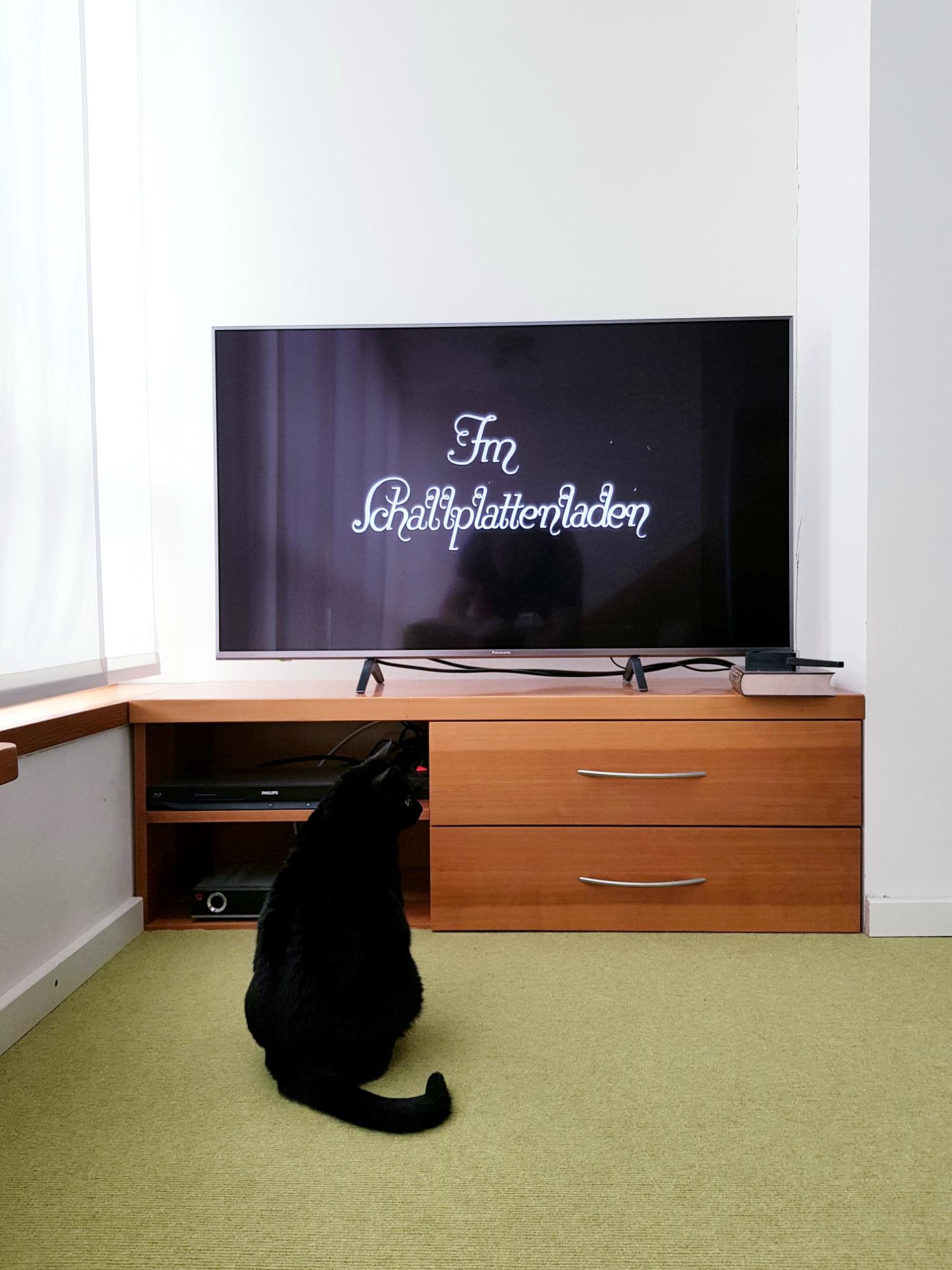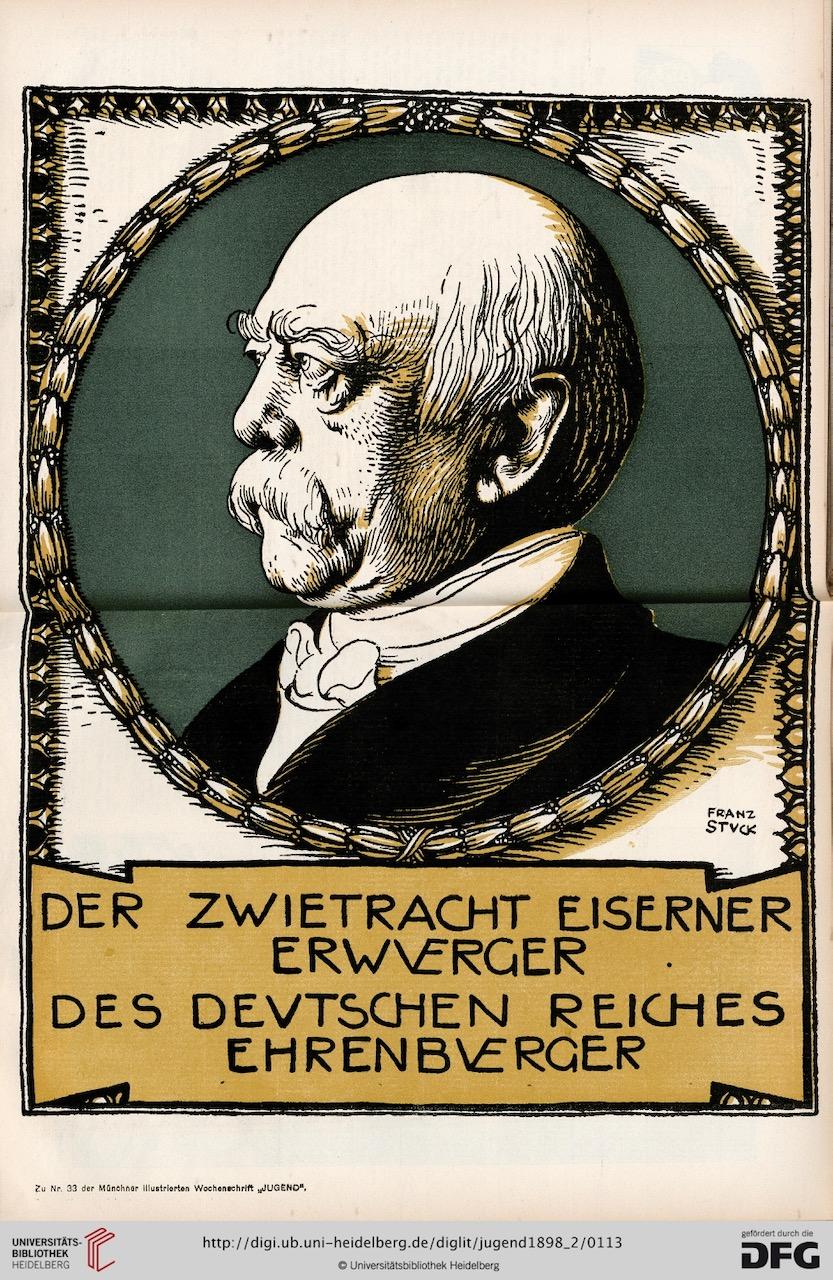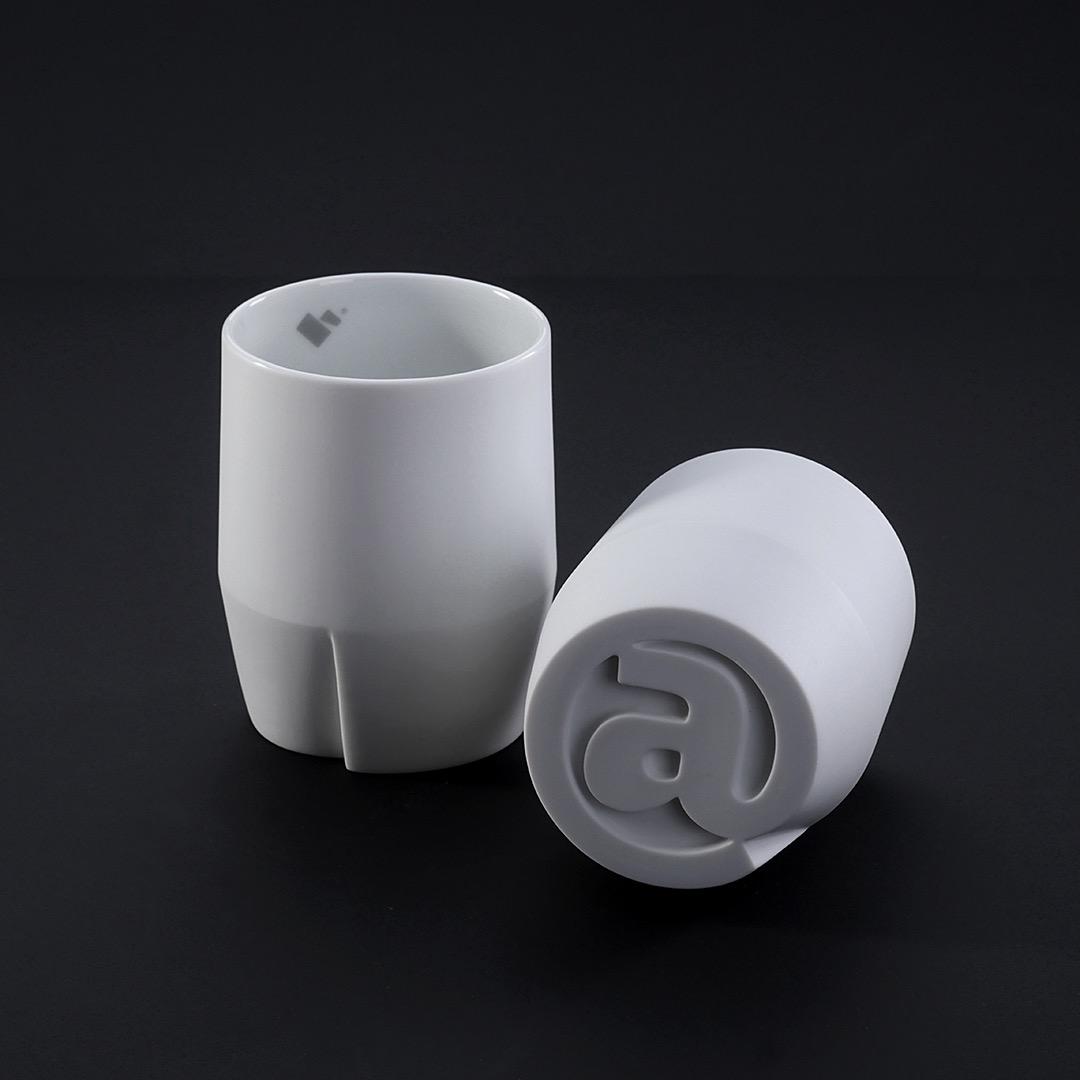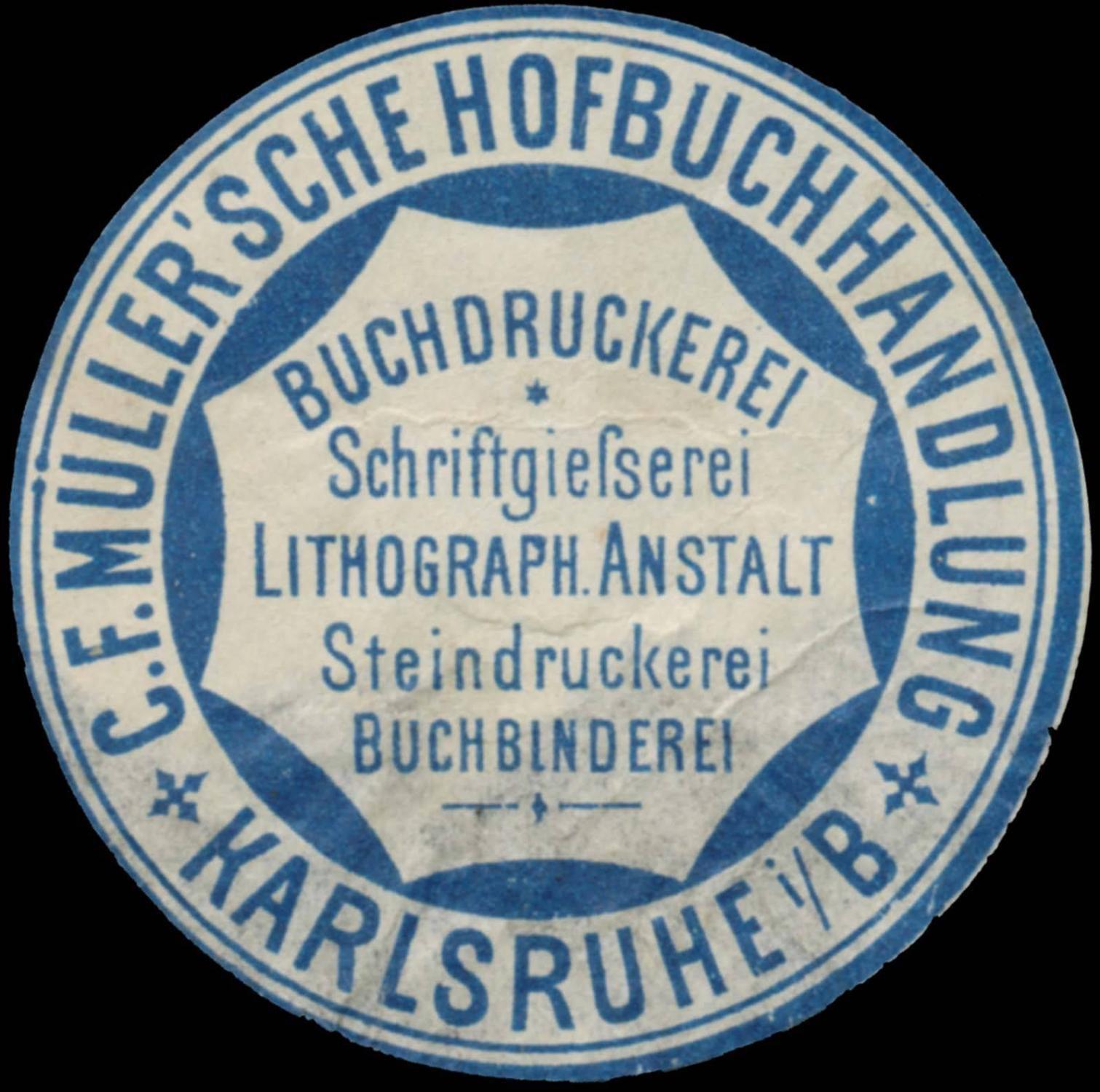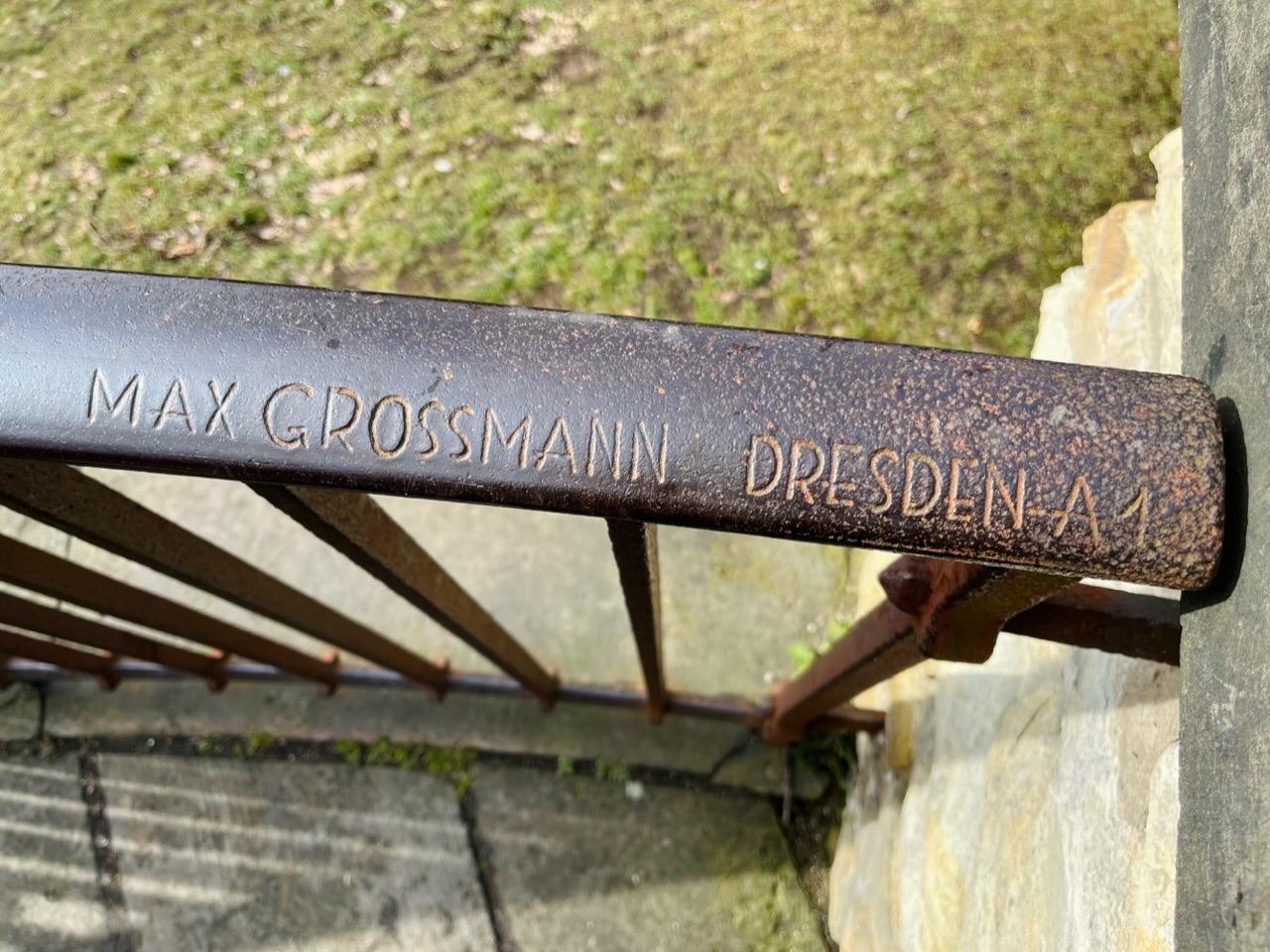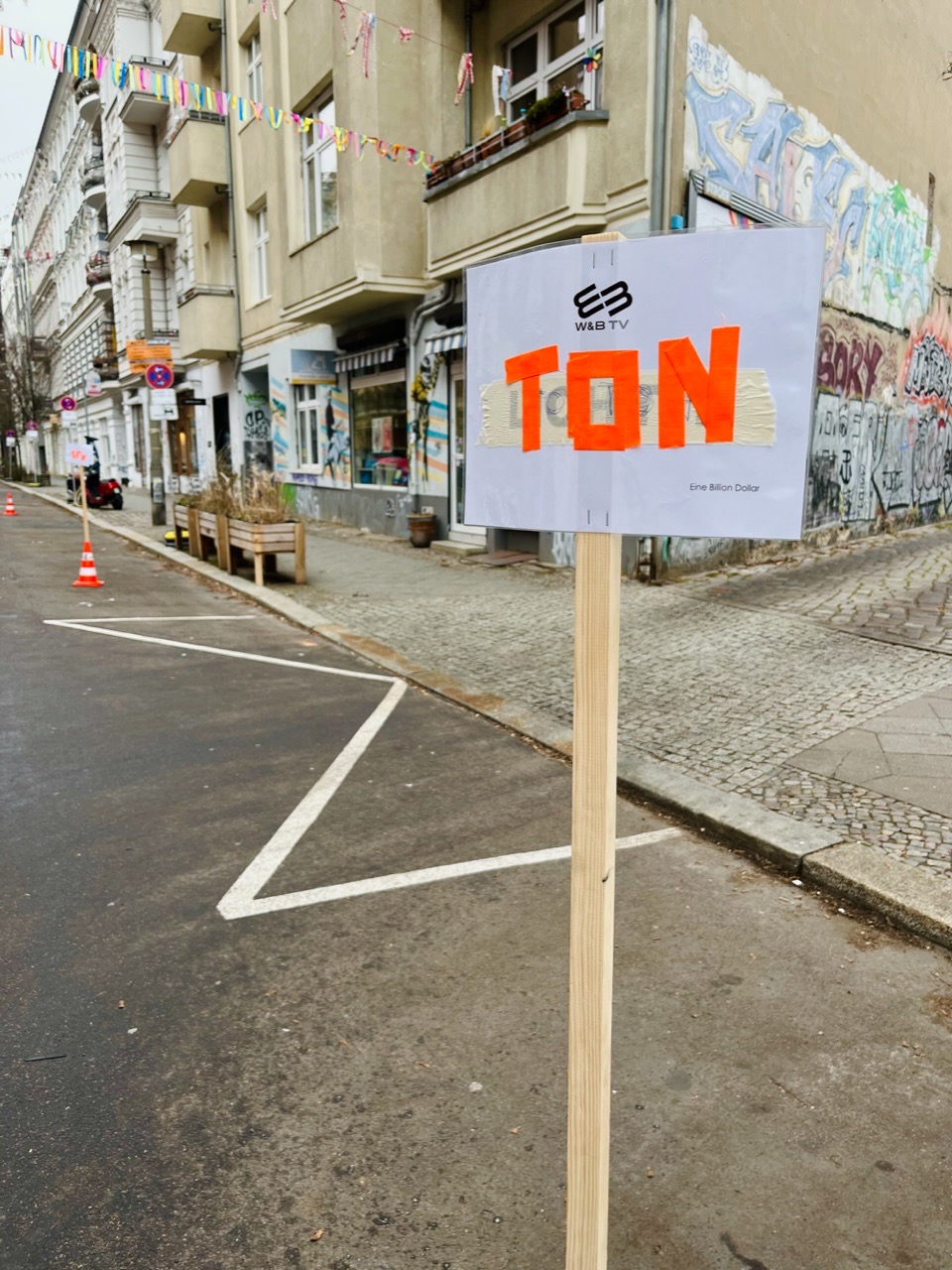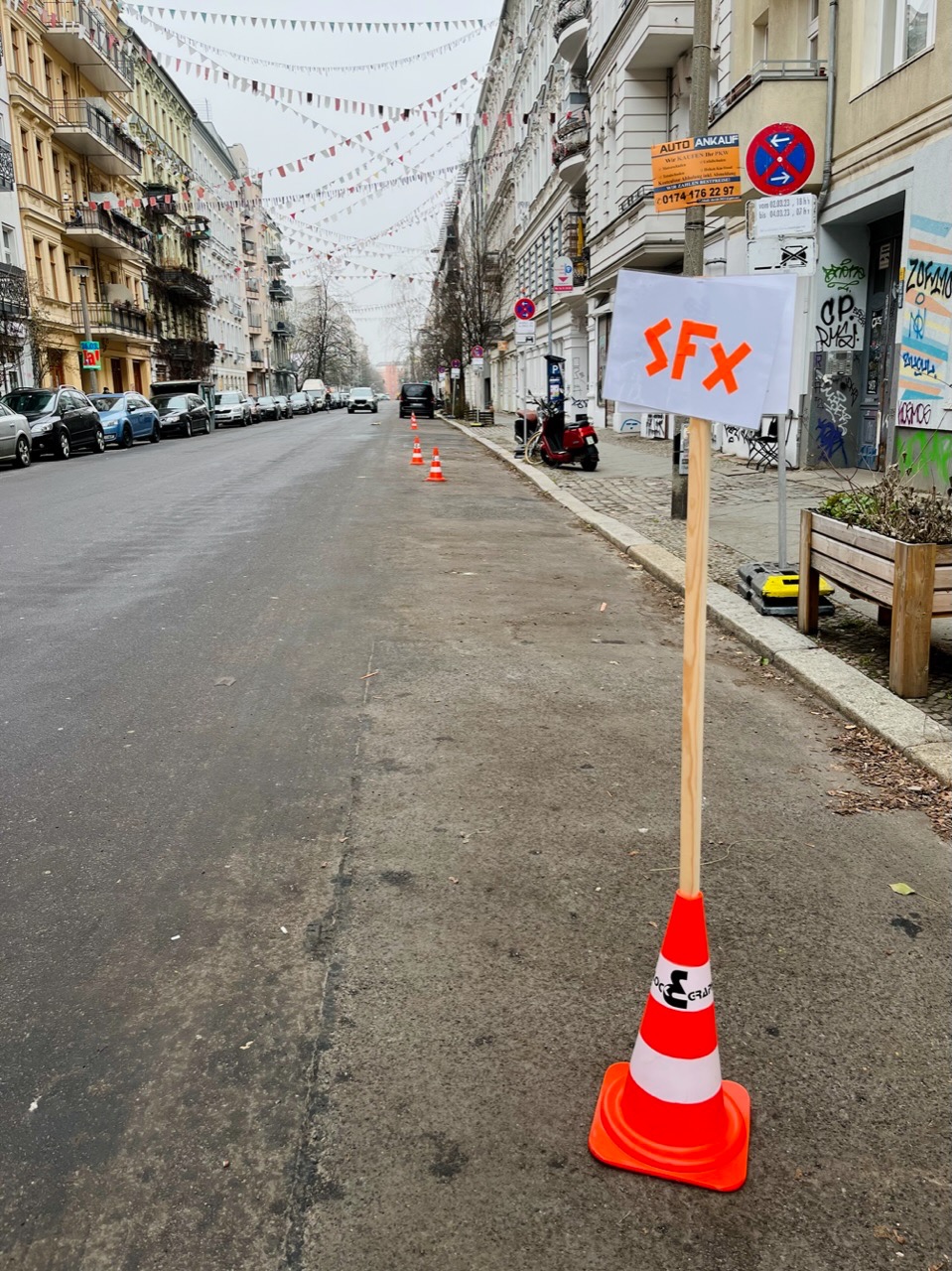
Weizenin ist Weizenstärke, kein Mehl. Damit werden die Kuchen fluffiger, einfach ca. ein Viertel der Mehlmenge durch Speiſepuder ersetzen. Kannst aber auch wie jede andere Stärke verwenden zum Binden von Soßen, Desserts etc.
Speiſepuder
Bon heute nicht fit für das lange s. Ich lese immer Seifepuder und frage mich, wo das n ist …
Filmtitel 》Im Schallplattenladen《 mit Karl Valentin und Zuschauerin Leila 😻.20230121_161042.thumb.jpg.abbd770307f4eee556b81df161aeaefc.jpg
So 'ne Art Mondamin also ... Danke!
Stünde rechts das Katzenfutter, säße sie aber nicht mehr vorm TV! Man sähe nur noch eine Staubwolke nach rechts entfleuchen ...;-)
Da tummeln sich die chinesischen Tanzmäuse die sich Karl Valentin zur Zerstreuung seiner Hauskatze zugelegt hatte. Aber ein wenig typografisches Gespür hat Leila schon, so wie sie sich passend zur Schrift am Bildschirm den Schwanz zurecht gelegt hat.
das Einführen einer eigenen, zu individuellen Gestaltung die Adressaten verwirren bis abschrecken können.
Zum Thema Abschrecken: Ich konnte mich nicht an den Namen der Belle Lettres-Edition der Budé-Kollektion (bisher habe ich noch niemanden getroffen, der die Gestaltung (Beispiel-PDF) ansprechend fand) erinnern, daher war ich ein büschen am rumgoogeln und -lesen und habe tatsächlich eine Interpretation der Drucktype gefunden, die ich hier mal für die Font-Sammler verlinke: https://boberle.com/projects/greek-font/ (Fontforge-Dateien sind öffentlich, aber keine Lizenz dabei)
... und auch SVG-Dateien im ZIP, zumindest wohl der griechischen Buchstaben.
Im Fontforge-.sfd ist aber noch viel  mehr drin, bspw. eine recht umfangreiche lateinische Belegung, keine Ahnung was und woher, sehe da keine Infos, ist aber auch schon ewig her, dass ich Fontforge mal gestartet und drin rumgewühlt habe ...
Die Ü-Torque ist auch nicht schlecht ...
Das ß dürfte aus der Übergangszeit sein, wo die Sulzbacher Form noch nicht definiert war ...?
Falls jemand einen typografischen Kaffee/Tee-Becher sucht ... hier ist er. Einen passenden Untersetzer gibt es auch.
Und wenn man kleckert auf das Papier ... ;-):-)